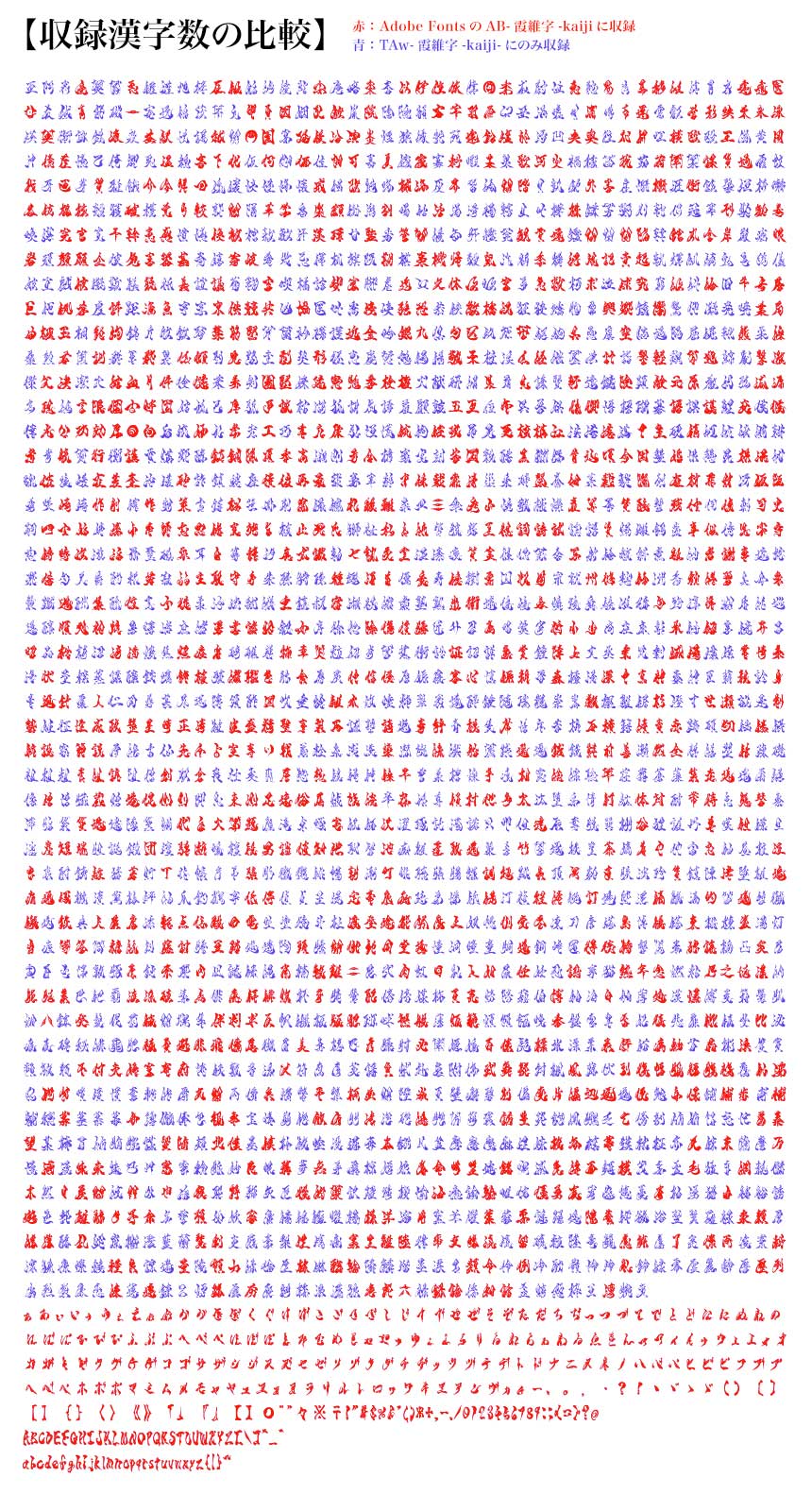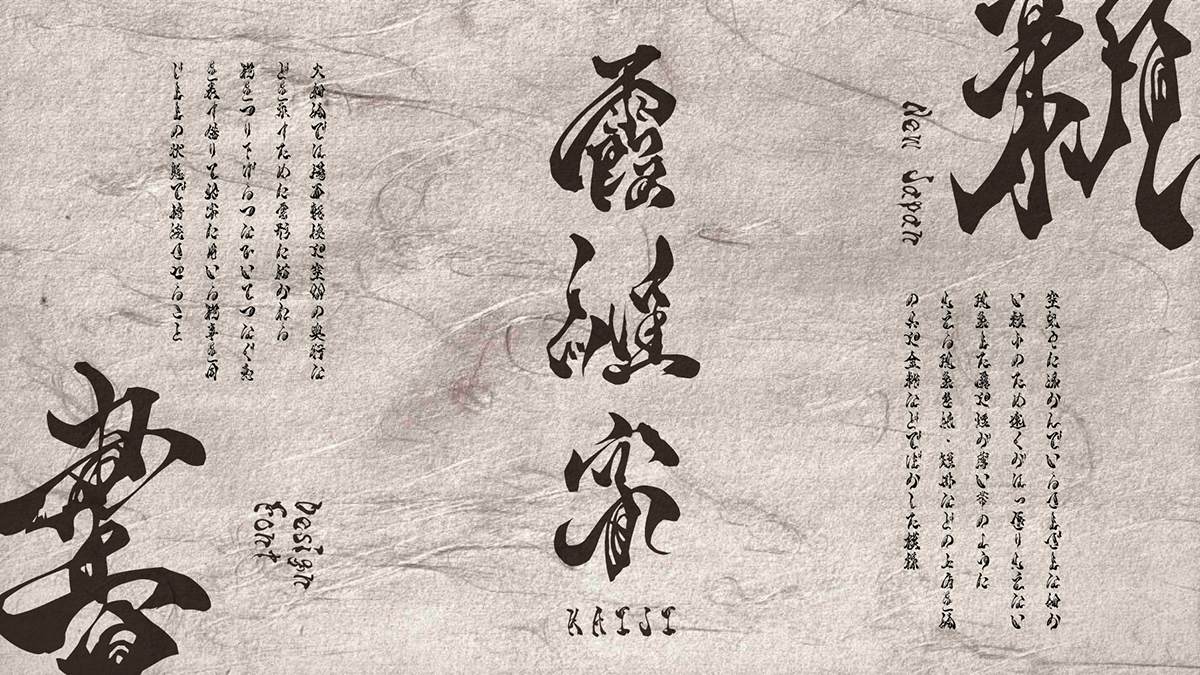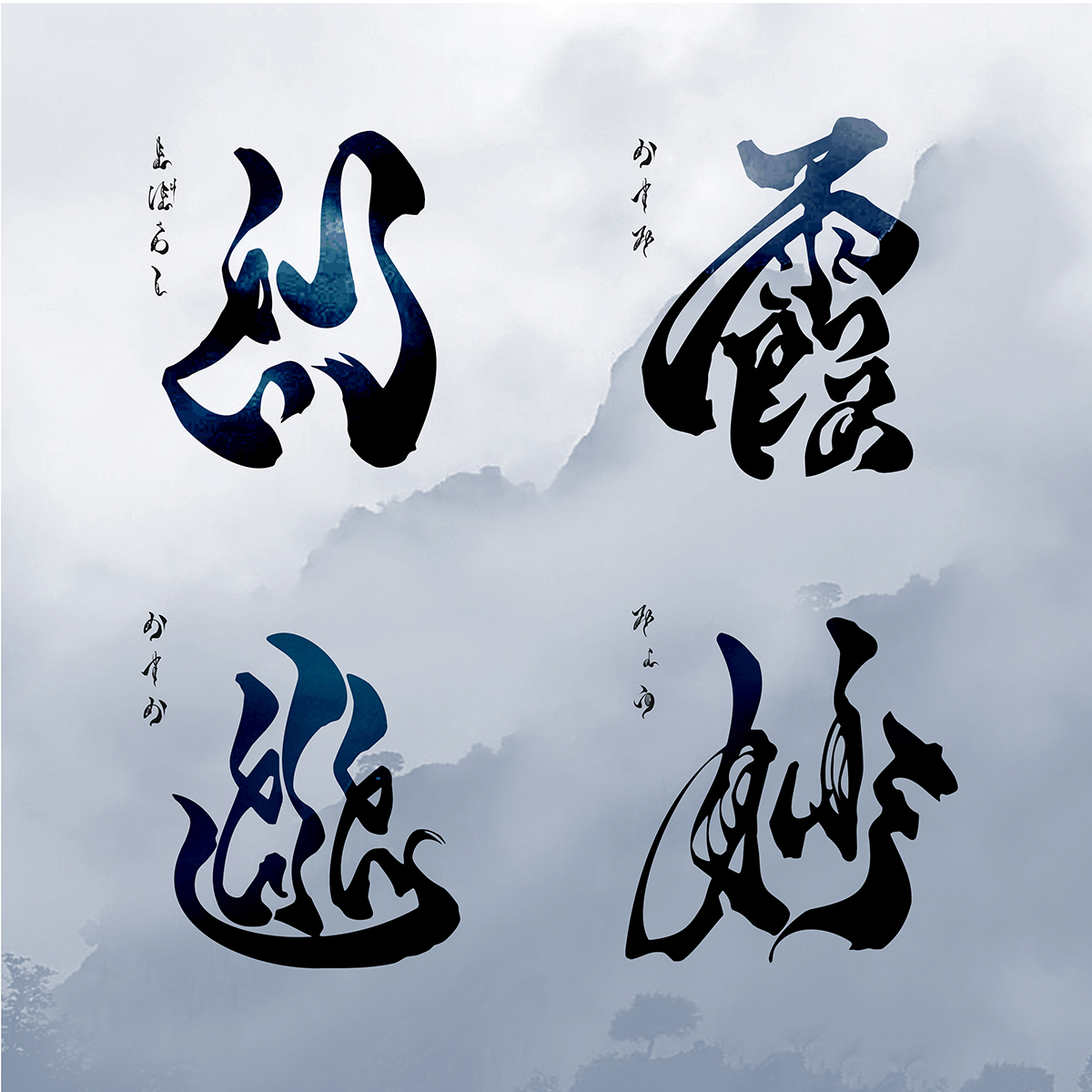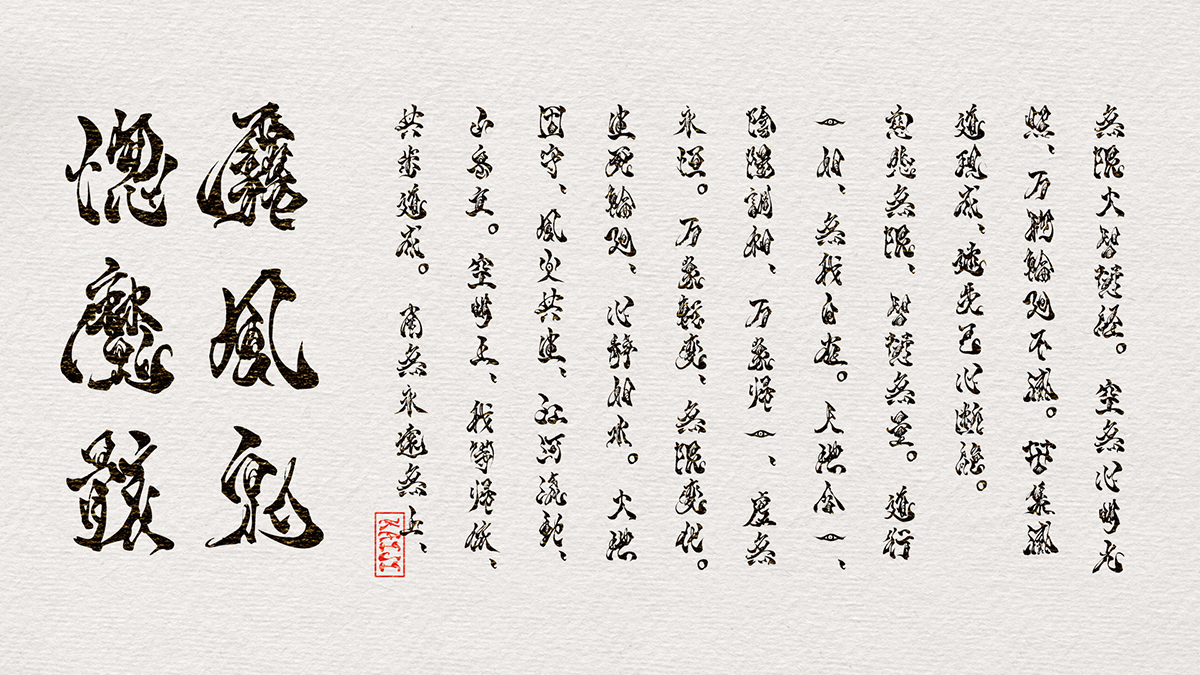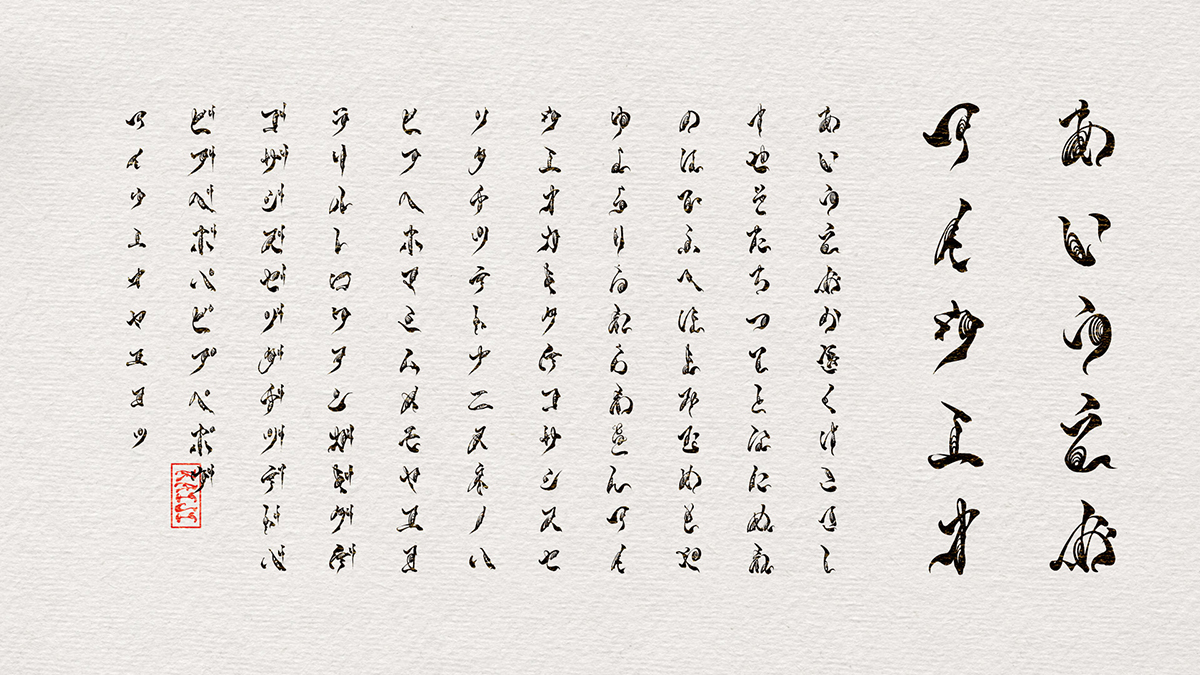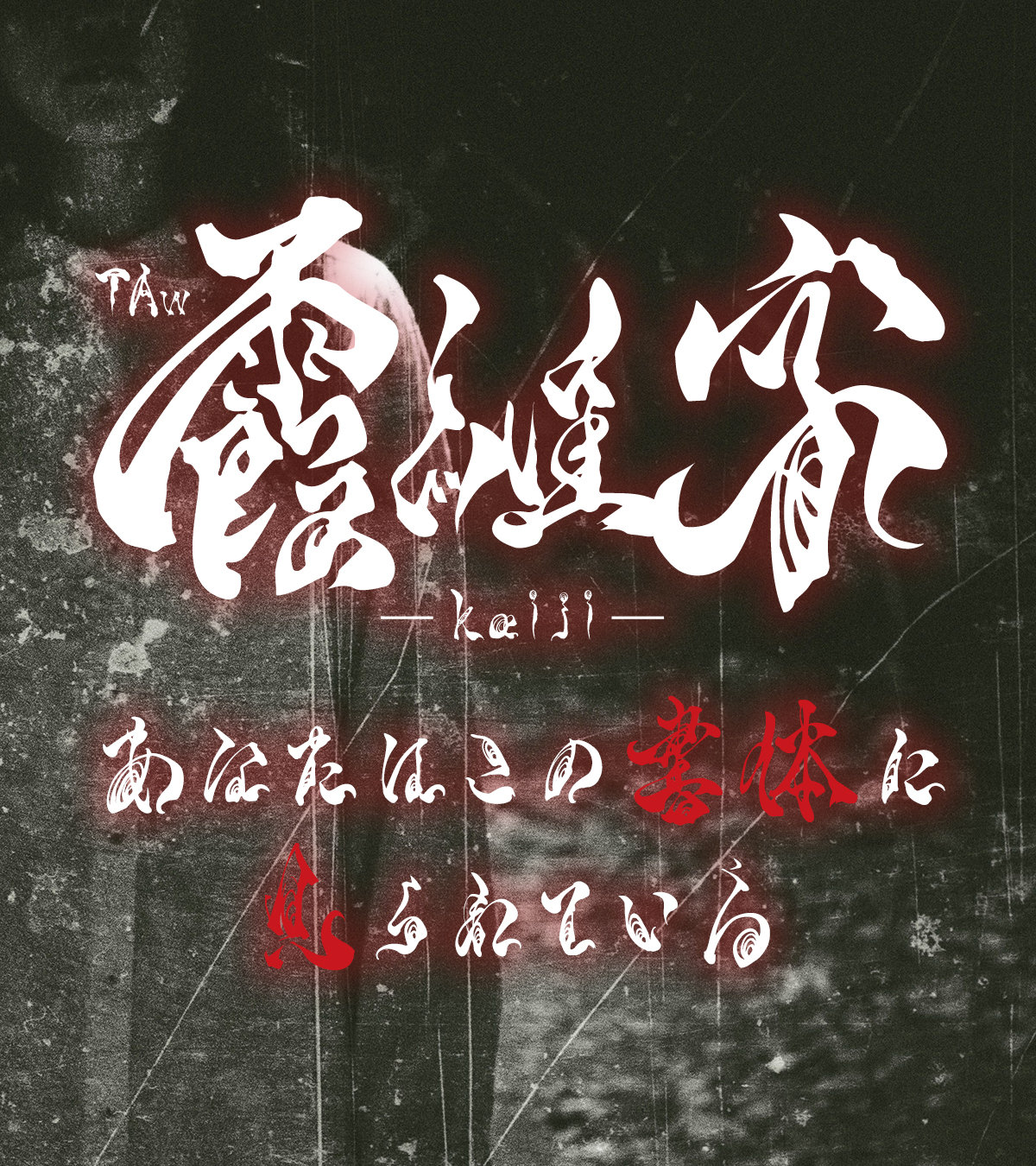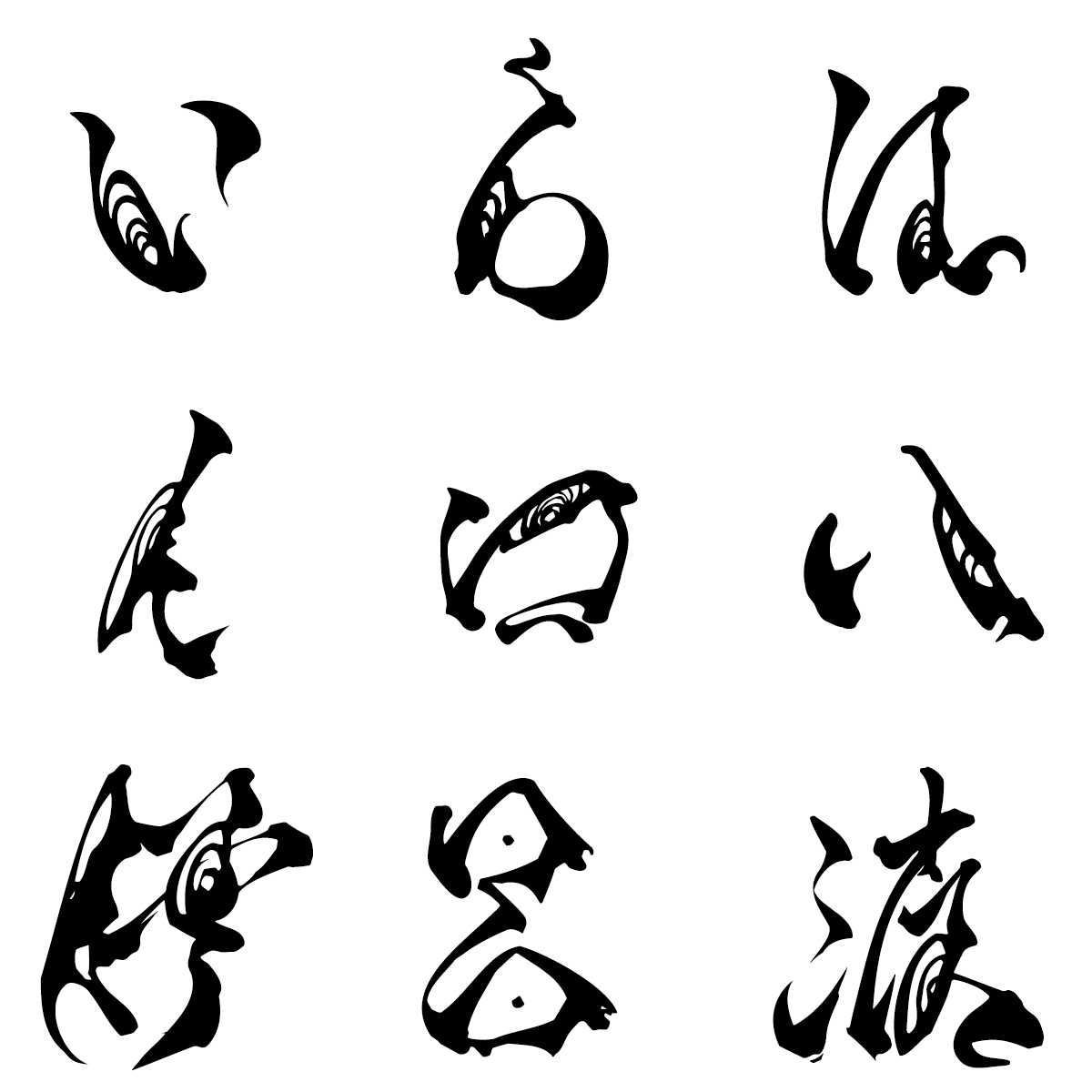
TAw-霞維字-kaiji- かいじ これは、ただの筆文字フォントではない。読まれることを拒み、存在を刻み込む、異形の筆文字。
「TAw-霞維字-kaiji-」それはとても恐ろしい筆文字書体
「TAw-霞維字-kaiji-」 これは、ただの筆文字フォントではない。
瞬間的に“文字”と認識されながらも、意味を読み取るには思考を強いる。読まれることを拒む、異形の筆文字。──そんな不穏で妖しげな魅力を秘めた書体です。
目が合う。視線を感じる。「目」の意匠が織り込まれたデザインは、まるで見られているような錯覚を生み、観る者の記憶に焼きつきます。意味を伝えるのではなく、存在を刻み込む。唯一無二の独創的なデザイン。
フォントとしてはもちろん、謎めいた背景グラフィックとしても活用可能。読む者を惑わせ、恐怖と興味を同時に抱かせる、新感覚の筆文字書体です。
「TAw-霞維字-kaiji-」の概要
ホラー筆文字フォント TAw 霞維字 かいじ 書体見本
「TAw-霞維字-kaiji-」とは?
視線を奪い、読む者を惑わせる──「TAw-霞維字-kaiji-」
TAw-霞維字-kaiji- かいじ の作者 無道 水墨画
「TAw-霞維字-kaiji-」は、視覚に訴えかける異質な存在感を放つ筆文字フォントです。
人形や水墨、創作文字を通じて“見えないものを見せる”表現を追求してきた無道さんが、読む者に違和感と集中を促すことを狙い制作。文字として認識されながらも即座には読めず、視線を止めさせ、「読む」ではなく「魅入る」体験を与えるフォントに仕上がっています。
可読性をあえて抑え、意味の伝達よりも視覚的な印象と感情の揺らぎを重視した本作は、従来のフォントの概念に挑む、唯一無二の書体です。
制作された無道さんに「TAw-霞維字-kaiji-」についてお話を伺いました。
無道さんについて
水墨にて「情報を見る」事を主とした表現をしている。
主体を変える事で見え方を変え、個の持つ知識によって解が生まれ、 自身が見る世界と他者が見る世界の違いを表現し、 1つに複数の意味を乗せる事によって見えないモノを見せる作品を制作。
フォント制作のきっかけ
元々は球体関節人形・絵・表現の思想を相手に伝える為に『「私」というフィルターを通して作品各々の世界を現実に表現している』 という目的があって創作文字や絵に忍ばせる文字等々を使っていました。
別の言語(作品たちの世界)→私(再解釈・翻訳)→日本語変換してるので、現実世界の美術史や倫理観は一切関係ありませんという防御策でした。
そんな中、もっと表舞台に出る為に、私の作品が企業様達にはどう判断・映るか、通用するかをクリエイターEXPO(クリエイターが集う展示会)に出展して反応を確認していた際、霞維字の原型になった手書きの文字を見て、ウェブフォントジャパンさんから声をかけて頂き、可読性の低い文字にも関わらず、フォントとして制作してみませんか?というお声を頂いたので、そのチャレンジ精神に答えようと思ったのがきっかけです。
クリエイターEXPOにて出展した際の会場での評価が「個人的には好きだが、会社でとなると…」「商品でどう使うか想像できない」「前例がない」 という言葉が多く投げかけられたので、印象が強かったです。 それもあって企業様が挑戦して頂けるのであれば、私が全力出さない訳にはという気持ちでした。
どんなフォントを作りたかったのか
TAw-霞維字-kaiji- かいじ を作ろうと思ったきっかけ
五感と文字認識の関係
人は慣れると視覚や聴覚等の五感本来の情報ではなく、自分を通したフィルターで感じる様になります。これはほぼ確実に確定した「形」に文字があるから可能であります。故に、流し見でも速読でも違和感なく読む事が可能になります。
私を読めという能動的な「魅入る」文字
逆に言えば、視点を止めずともいい訳です。それでは、文字から相手方を考え、読み取る行為が弱まってしまうので、 強制的に違和感を覚えさせ、視点を止めて、読むだけでなく、見るだけでもない「魅入る」文字を目指しました。
要約すると、文字という「存在」として、私を読んでという「受け身」から、私を読めという「能動的」な立ち位置にしたかった。
多層的な読解体験を設計する
人形の物語を小説にしたいと思った時に、翻訳したズレを表現したいと思って仕掛けを施した本を作ってみました。
読み方として、速読・斜め読み・飛ばし読み・数列同時読み等ありますが、これらを使って読んだ場合に別の意味でも読めるような小細工。文字配列を弄り、列の幅や余白を調整して、文と文が途中で繋がるような形にし、多角的に捉えられるようにしました。
個人の解釈と対話体験を促す試み
この意図は解釈の仕方・捉え方は人それぞれ異なる。それは対話し気が付く事で在りますが、それを個人で実感できるようにして見たかった。
読む動作と見る動作は目線移動と思考が違いますので、文として読む理解と目で見た印象の理解。
こういった1つのモノに対し、多角的に捉える事を文章でも表現したのがきっかけになりました。
制作の流れとフォント誕生まで
制作着手順 造形→本・文字→水墨
人形を作ったから、そのキャラの背景を表現する為に小説や創作文字を作る事になって、人形や文字を作ったから、形、情報を削った状態の水墨表現を使うようになって、再構築して出来たのが今回のフォント。
霞維字の制作のこだわり
TAw-霞維字-kaiji- かいじ のこだわりのポイント
文字のフォント化に向けた崩し方の工夫
文字をフォント化した場合の出来を見せてもらったので、太さ等を考慮しつつどう崩すかを考えて、入り方と強弱、密度を見ながら、目に見えるように考えて同じ部首や漢字が入る文字で練習して書いてました。
筆道具へのこだわりと使い分け
私は道具によって結構変わってしまうタイプなので、筆は同じ物を何本も買って使ってました。同じ筆でも違いがあるので、ワザと摩耗させたりしてました。文字によっては筆を変えたりして表現変えたりも。
墨の調整と制作環境への配慮
墨は主に冬に制作していたので、気温によってサラサラ糸と粘度の高いものを混ぜて乗りやすい状態を探ってから本番へ。
「TAw-霞維字-kaiji-」の特徴
「目」の意匠が織り込まれたデザイン
TAw-霞維字-kaiji- かいじ 「目」の意匠が織り込まれたデザイン
随所に、意図的に「目」を想起させるデザインが組み込まれており、それが不気味な存在感を生み出します。
筆の流れの中に潜む鋭い曲線、線の断片が生み出すまなざしのような形状、そして滲んだかすれがまるで見開かれた瞳のように映る。これらの要素が絡み合うことで、無意識に「見られている」という感覚を抱かせ、文字以上の情報を視覚的に伝達します。
Adobe Fontsで提供されるAB-霞維字-kaijiとの違い
Adobe Fontsで提供されるAB-霞維字-kaijiの収録漢字が常用漢字ベスト1,000文字なのに対し、デザインポケットで取り扱っているTAw-霞維字-kaiji-は、JIS第一水準(2,965文字)までを収録しています。
TAw-霞維字-kaiji- かいじ とAB-霞維字-kaiji かいじ との違い
上の画像で赤い文字は、AB-霞維字-kaijiに収録されている文字。青い文字は、TAw-霞維字-kaiji-にのみ収録されている文字です。Adobe Fontsで提供されているABシリーズでは収録漢字が半分以下となっています。